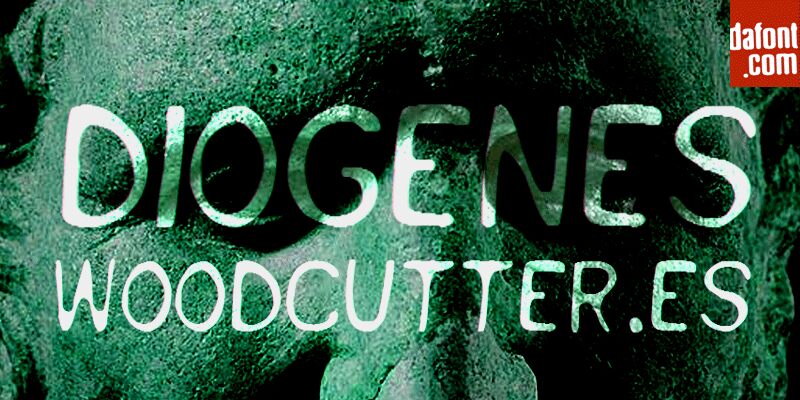
Diogenes von Woodcutter Manero ist eine kostenlose Display-Schrift mit abgenutzter Optik; sie sieht aus, als wäre sie aus weichem Linoleum geschnitten und mit trockenem Farbauftrag veredelt worden. Die Striche wirken füllig und leicht unruhig, mit krümeligen Aussparungen und abgerundeten Kanten, die jedem Wort einen handgemachten, verwitterten Rhythmus verleihen.
Verwenden Sie Diogenes für ausdrucksstarke Titel auf Konzertplakaten, Zines, Album-Covern, gruselig-verspieltem Branding, Verpackungen für Handgemachtes oder Designs für Aufkleber und T-Shirts. Diese kostenlose Schriftart glänzt auch in Social-Media-Headern, wo die Textur wichtiger ist als reine Perfektion. Kombinieren Sie sie mit einer klaren serifenlosen Schrift wie Inter oder Helvetica und setzen Sie Diogenes etwas größer mit zusätzlichem Laufweiten-Abstand, damit die Rauheit gut lesbar bleibt.
Diogenes